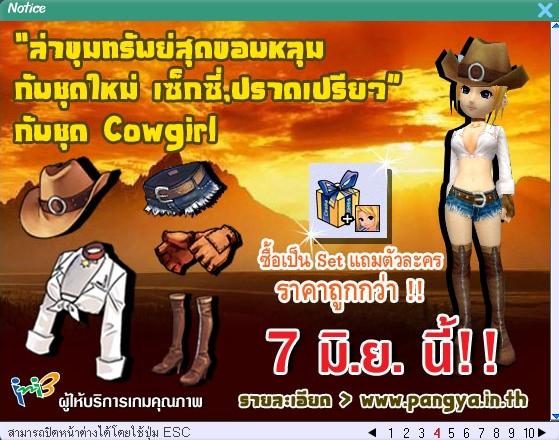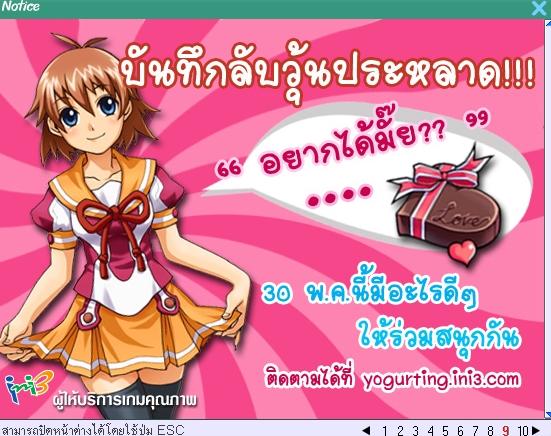
ปังย่า
เพิ่งมีวันนี้ค่ะ
เอ๊ะ เมื่อวานดิ  :08:
ไม่แน่ใจว่าฟอนต์ลายมือนี่ของใคร
/ :08:
อันนี้ ให้ดูเฉยๆ ค่ะ  :08:
ทำไมพี่แอนทำฟอนต์เลขศูนย์ต้องมีจุดตรงกลาง
กันคนสับสนกะตัวโอเด่ะ
แบบเนี้ย
f0nt
|<3N
วงรีผอมๆสูงๆคือเลขศูนย์ฮินดูอารบิก ตัวรีเกีอบกลมใหญ่คือตัวโอพิมพ์ใหญ่ ตัวรีเกีอบกลมเล็กคือตัวโอพิมพ์เล็ก ตัวกลมหรือรีเล็กน้อยส่วนใหญ่มีขนาดเพียงครึ่งบรรทัดคือเลขศูนย์ไทย หากมีจุดตรงกลางและอยู่กลางบรรทัดเป็นฟองมันครับ
เลข 0 ในดอสมีจุดตรงกลางนะครับ
อ๋อ ปังย่า